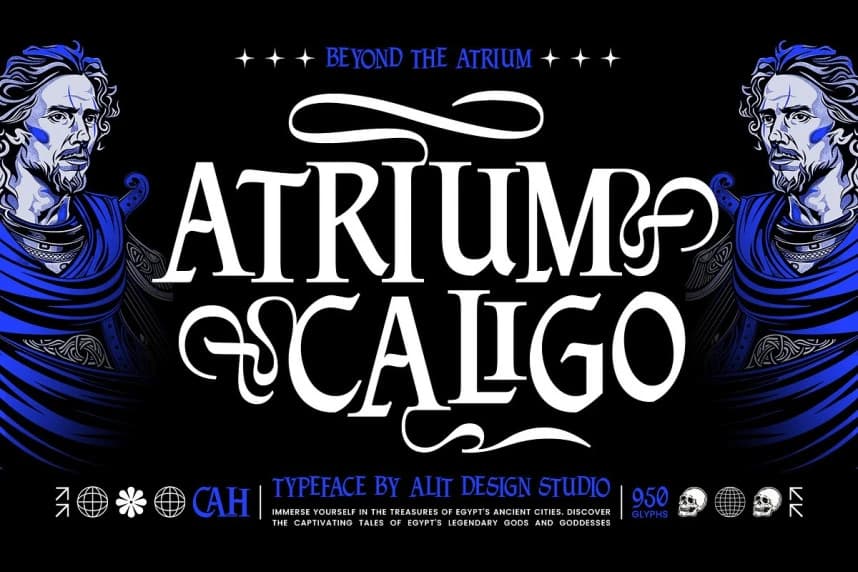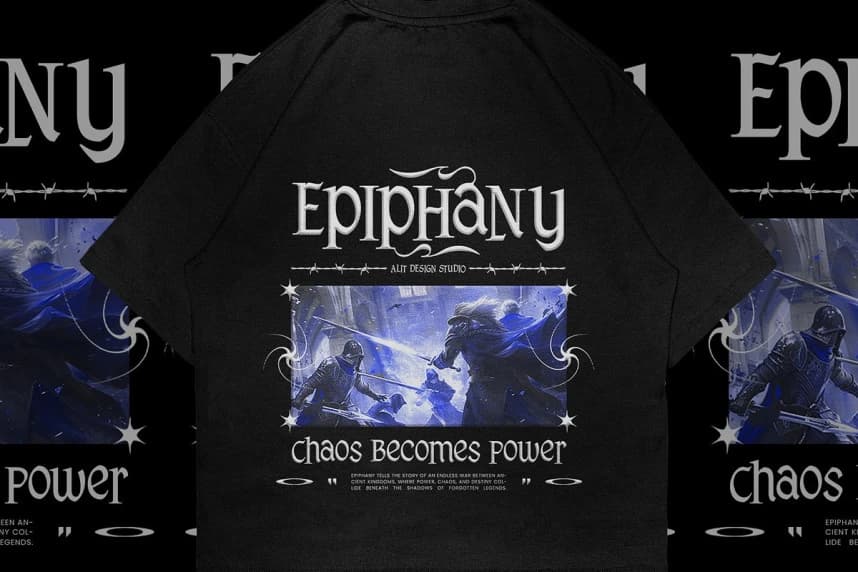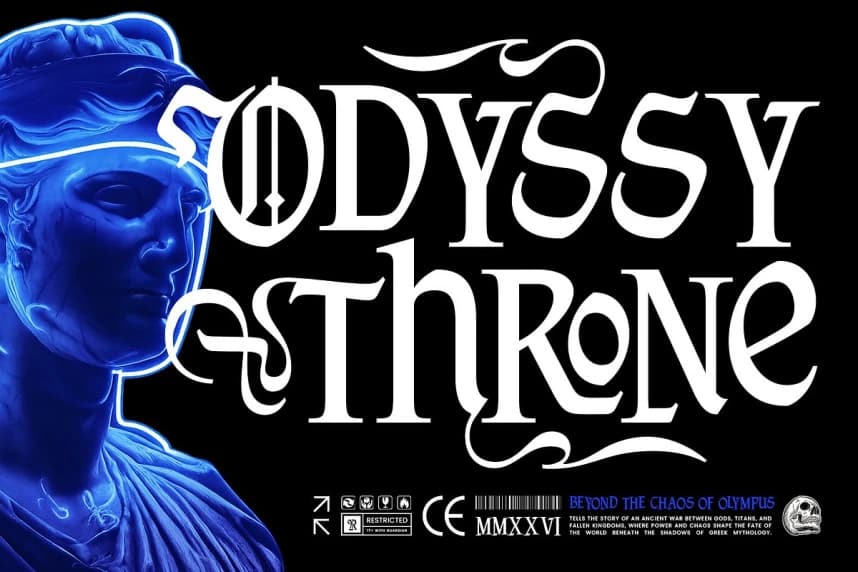
Virtus Gloria Font
Virtus Gloria Font, otorite, onur ve zamansız zarafet gerektiren tasarımlar için tasarlanmış güçlü bir blackletter gösterim yazı tipidir. Antik Roma erdeminin ve mitolojisinin zamansız değerlerinden ilham alan bu yazı tipi, klasik Ortaçağ tipografisi ile çağdaş sokak şıklığı estetiği arasında bir kö
Virtus Gloria Font, otorite, onur ve zamansız zarafeti gerektiren tasarımlar için tasarlanmış güçlü bir blackletter yazı tipidir. Antik Roma erdeminin ve mitolojisinin zamansız değerlerinden ilham alan bu yazı tipi, klasik Ortaçağ tipografisi ile çağdaş sokak-şık estetiği arasındaki uçurumu kapatıyor.
Virtus Gloria